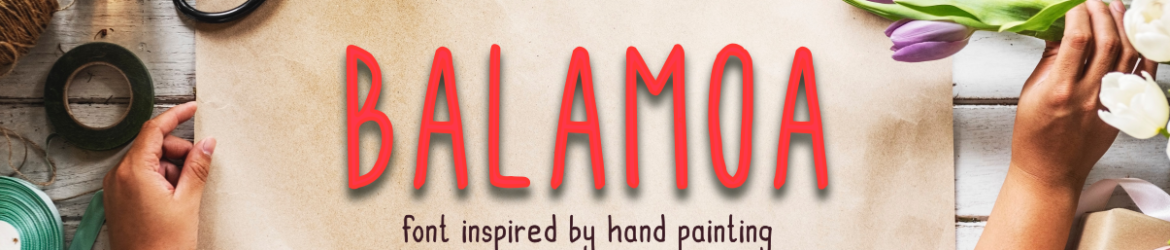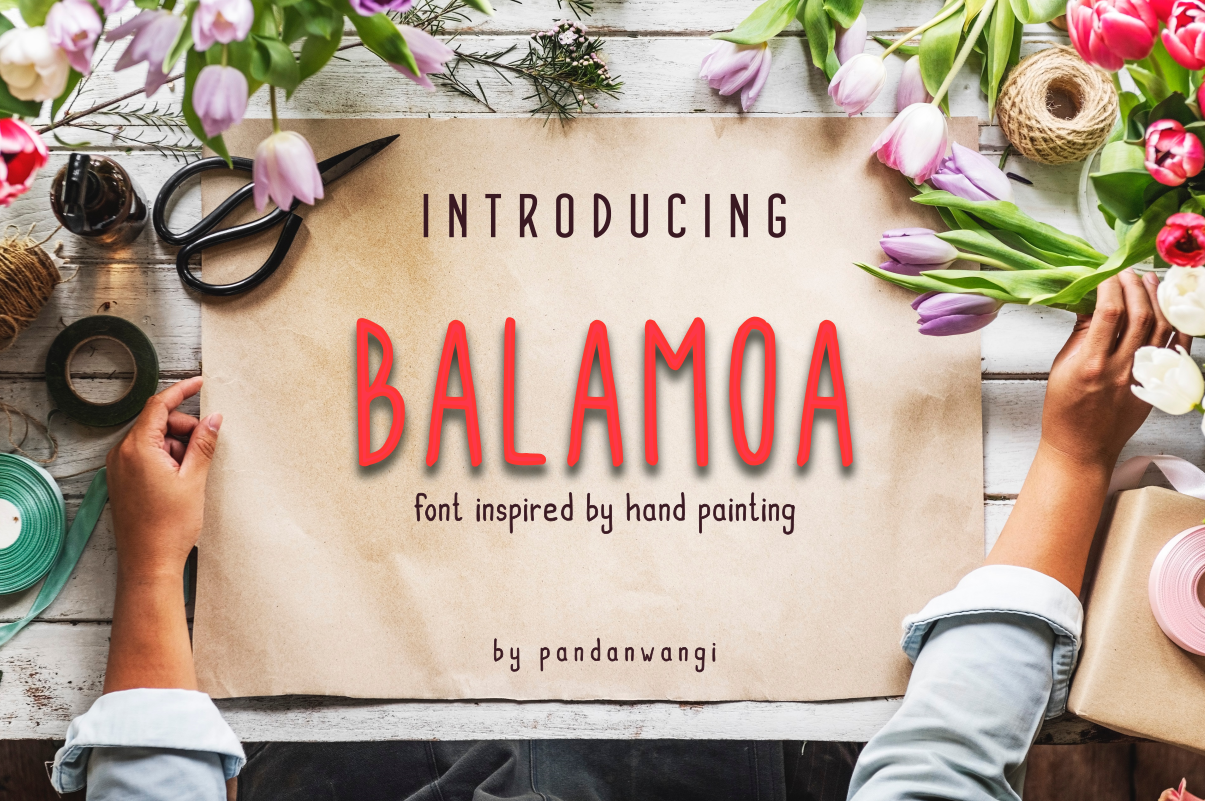
Balamoa Font Family
Descubra a Balamoa Font Family, uma famosa família de fontes escritas à mão que oferece diversão e sofisticação ao mesmo tempo. Esta famoso conjunto inclui quatro estilos perfeitamente combináveis: Regular, Italic, Bold e Bold Italic. A designer pandanwangi criou esta famoso família como uma experiência visual encantadora para todos os usuários de fontes. Os quatro estilos permitem que você personalize a aparência da sua página digital conforme preferir – seja com um texto suave e elegante, ou algo mais vibrante e descontraído. A Balamoa Font Family não é apenas uma coleção de letras; ela oferece uma experiência criativa, combinando facilmente diferentes estilos em cada projeto. Seja você designer gráfico, web designer ou mesmo escritor, a Balamoa oferecerá um toque especial à sua obra com seu design único e versátil. Vivencie o encanto da família de fontes Balamoa para adicionar um ar descontraído e colorido à sua composição visual. Sua diversão está aqui para você.
Designer: pandanwangi